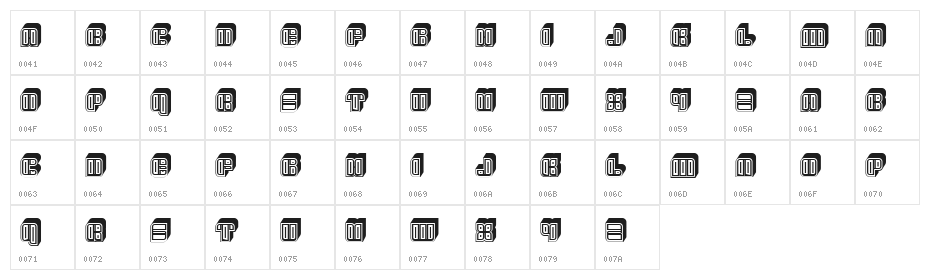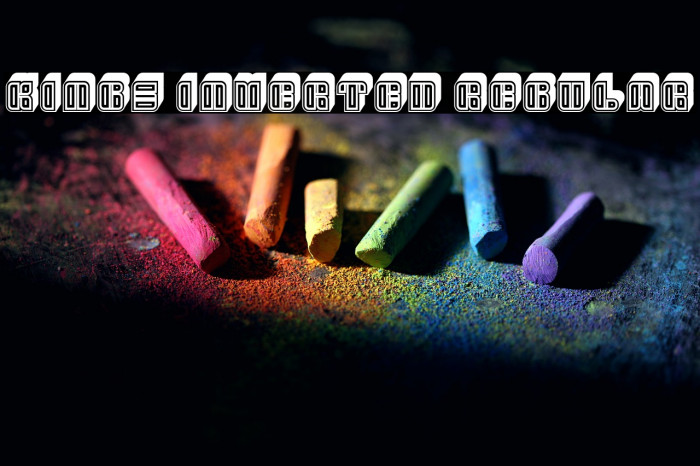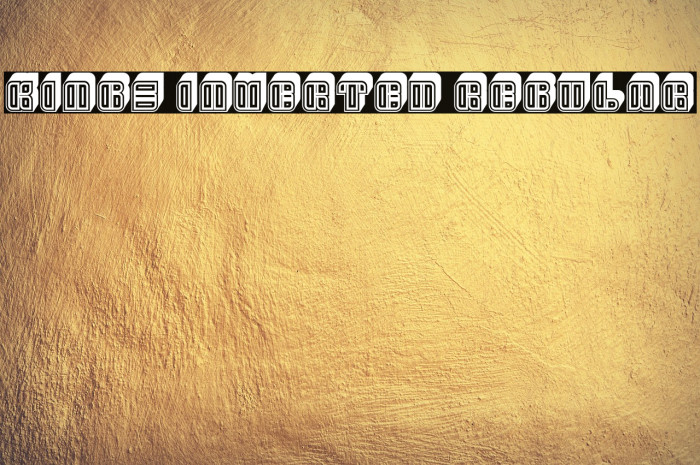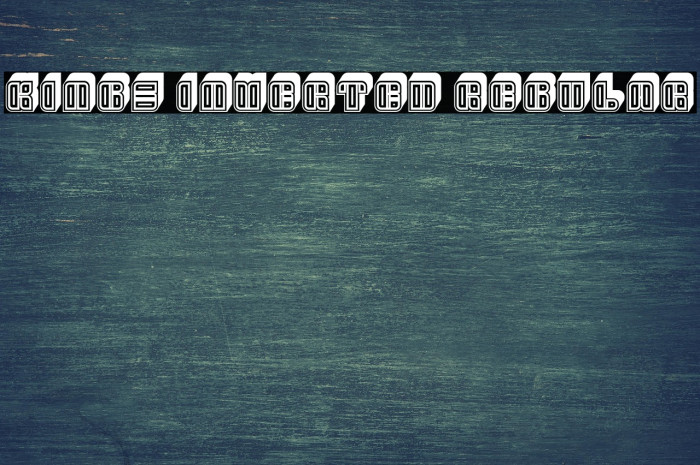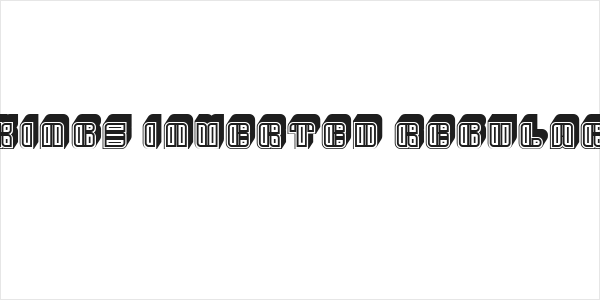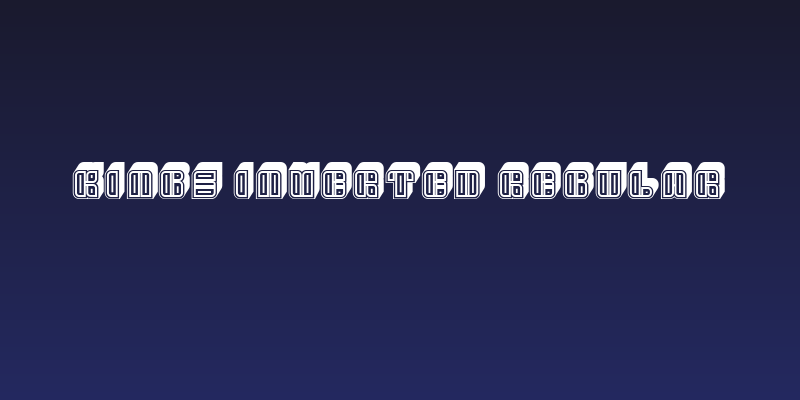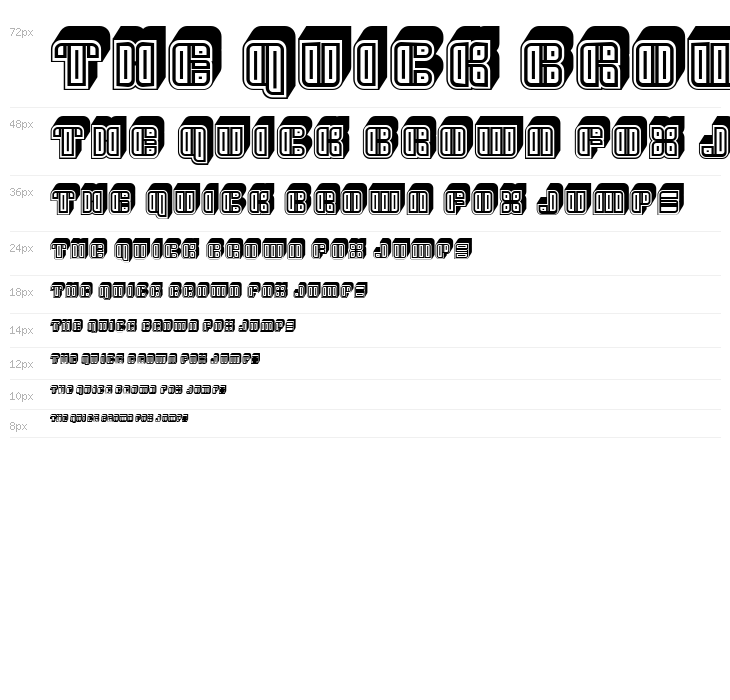
Kings Inverted Regular Font
| Stile generale | Futuristic, Digital |
| Progetti proposti | Ideal for posters, logos, video game titles, and any project requiring a futuristic or digital theme. |